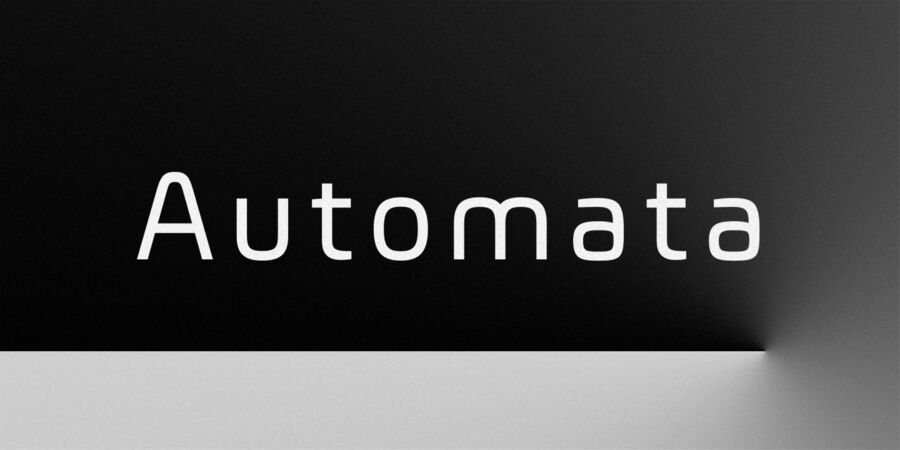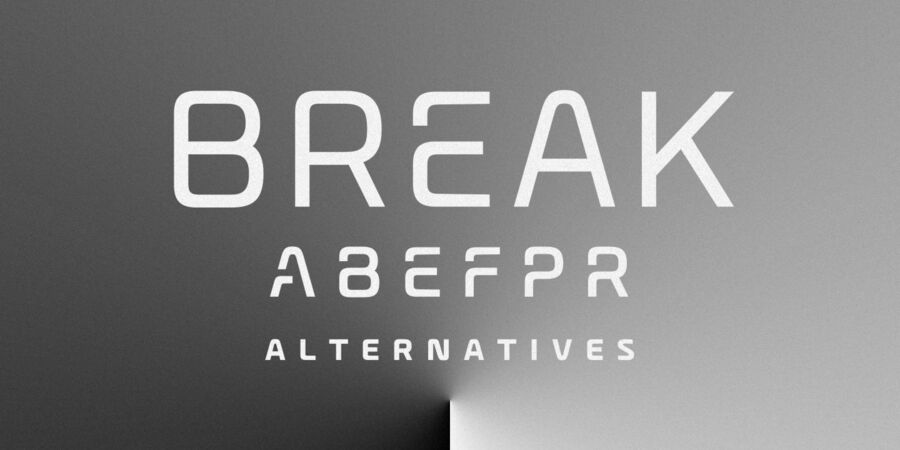
Опис гарнітури AutomataШрифт Automata поєднує сучасний вигляд із легкістю читання. Завдяки плавним, чистим лініям і геометричній естетиці Automata передає відчуття технологій та інновацій. Ми не пожертвували розбірливістю, тому Automata все ще легко читається на середніх і малих розмірах, що робить його придатним для широкого спектру застосувань.
На додаток до футуристичних елементів дизайну, Automata пропонує безліч додаткових налаштувань, як-от стилістичні альтернативи, круті дискретні лігатури та кілька варіантів накреслень різної ваги, в тому числі, надлегке та чорне. Підтримка багатьох мов робить Automata глобальним шрифтом.
Шрифт розробив Енріко Согарі у 2023 році.
Особливості сімейства шрифтів AutomataХіт десятиліття:
Асоціації з сімейством шрифтів AutomataОсобистість і характер гарнітури:
лаконічний, інженерний, точний, логічний, рівний, мінімалістичний, міський, якісний, західний, спокійний, сучасний, модний, комфортний, холодний, тонкий, легкий, ясний, чистий, невагомий, прозорий, худий, гладенький, скляний, крихкий, футуристичний, дротяний, неоновий, космічний, автоматичний, машинний, елементарний, гнучкий, урбаністичний, Простий, серйозний, статичний, стійкий, глобалізований, глобалістічний, зрозумілий, доступний, технічний, креслярський, непомітний, впевнений, надійний, спортивний, важливий, переконливий, стабільний, твердий, сильний, техногенний, М'який, мужній, індустріальний, крутий, амбітний, залізничний, сталевий, залізний, промисловий, потужний, авторитетний, помітний, важкий, сексуальний, прямокутний
прилад, гаджет, девайс, дизайн, креслення, чистота, технології, фантастика, інновації, айтішник, айті, IT, Місто, космос, техніка, наука, електроніка, астрономія, небо, вода, гра, урбаністика, транспорт, інтернет, мобільний зв'язок, інженер, аеропорт, метро, ліки, конструктор, медицина, математика, коворкінг, автомобіль, комп'ютерна гра, авто, автобус, паливо, Локдаун, логістика, інструмент, кіберспорт, спорт, аптека, промисловість, верстат, електростанція, енергетика, завод, тренажери, екшен, залізниця, іграшка, зореліт, розваги, атракціон, андроїд, залізо, металургія, мотор, двигун, робот, зброя, машинобудування, вантажоперевезення, вантажівка, шоу, телебачення, позашляховик, далекобійник, поліція, блокбастер, бойовик Гарнітура асоціюється з віком: